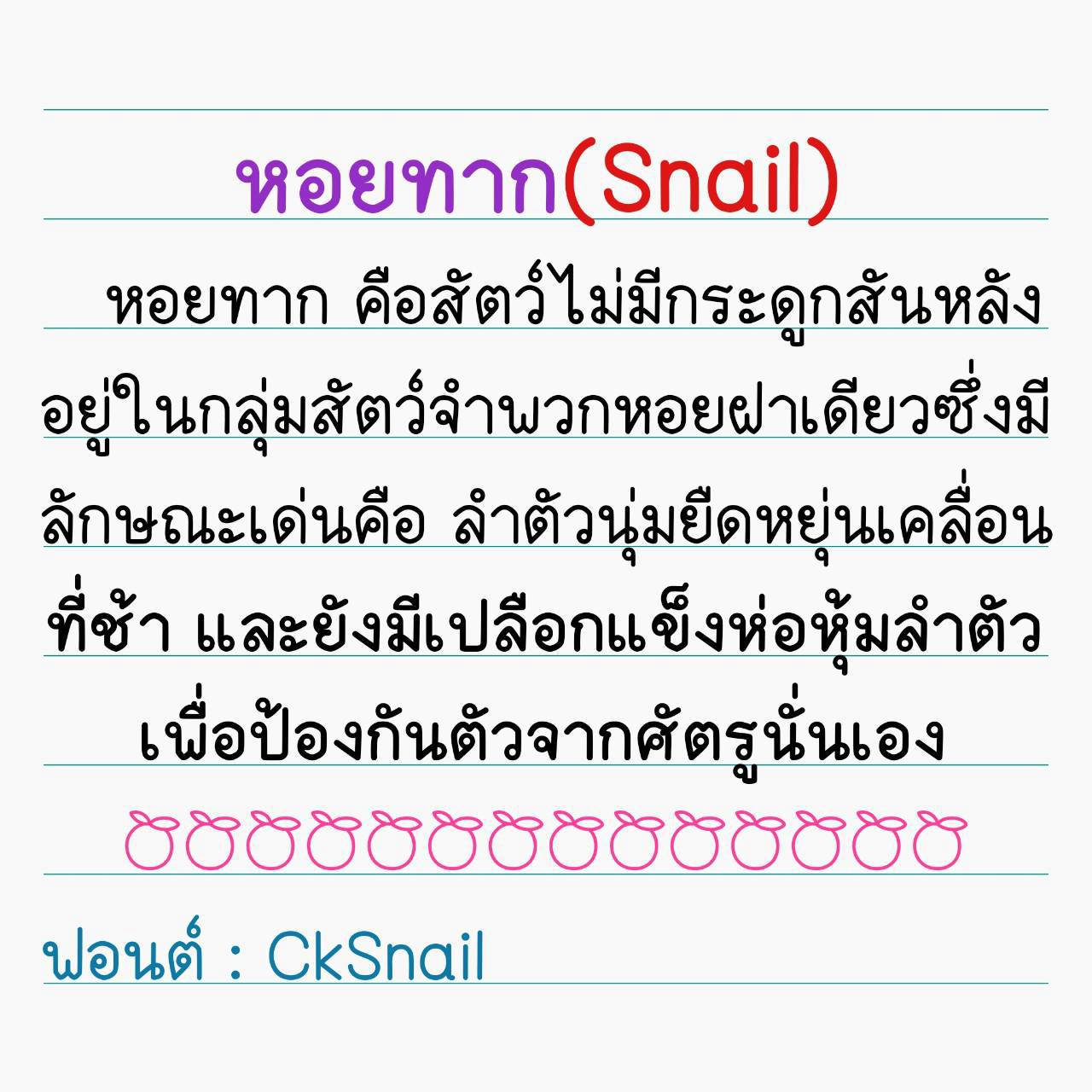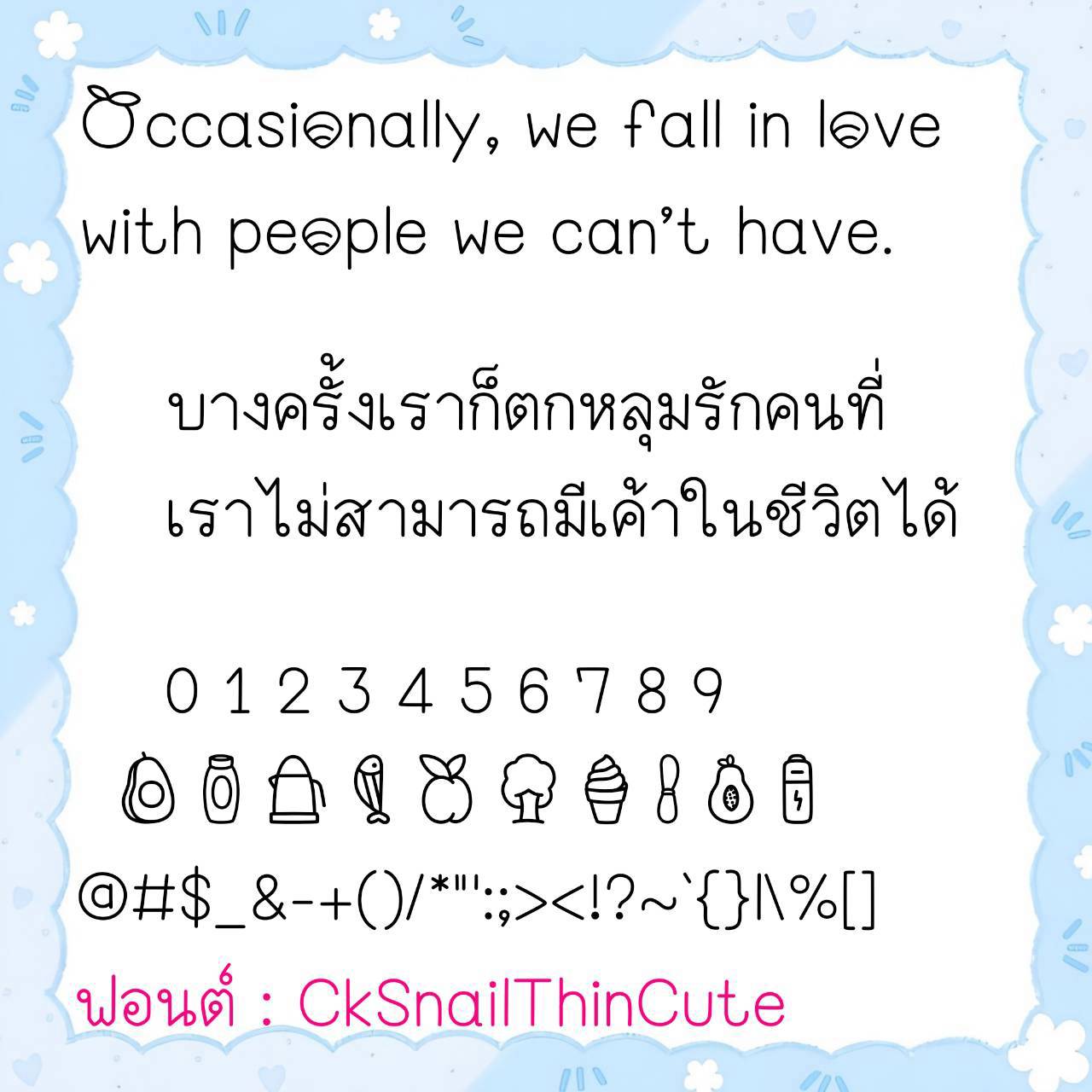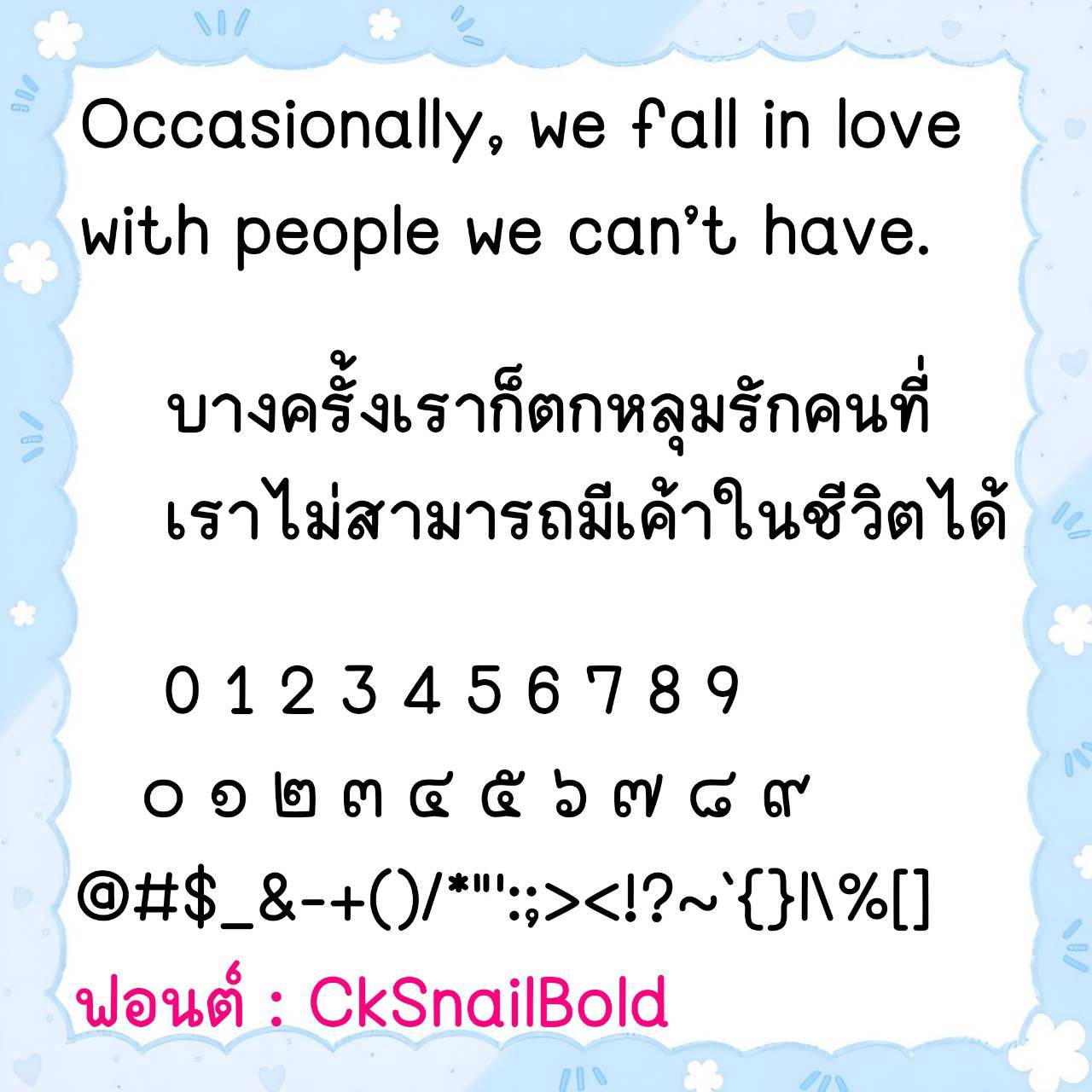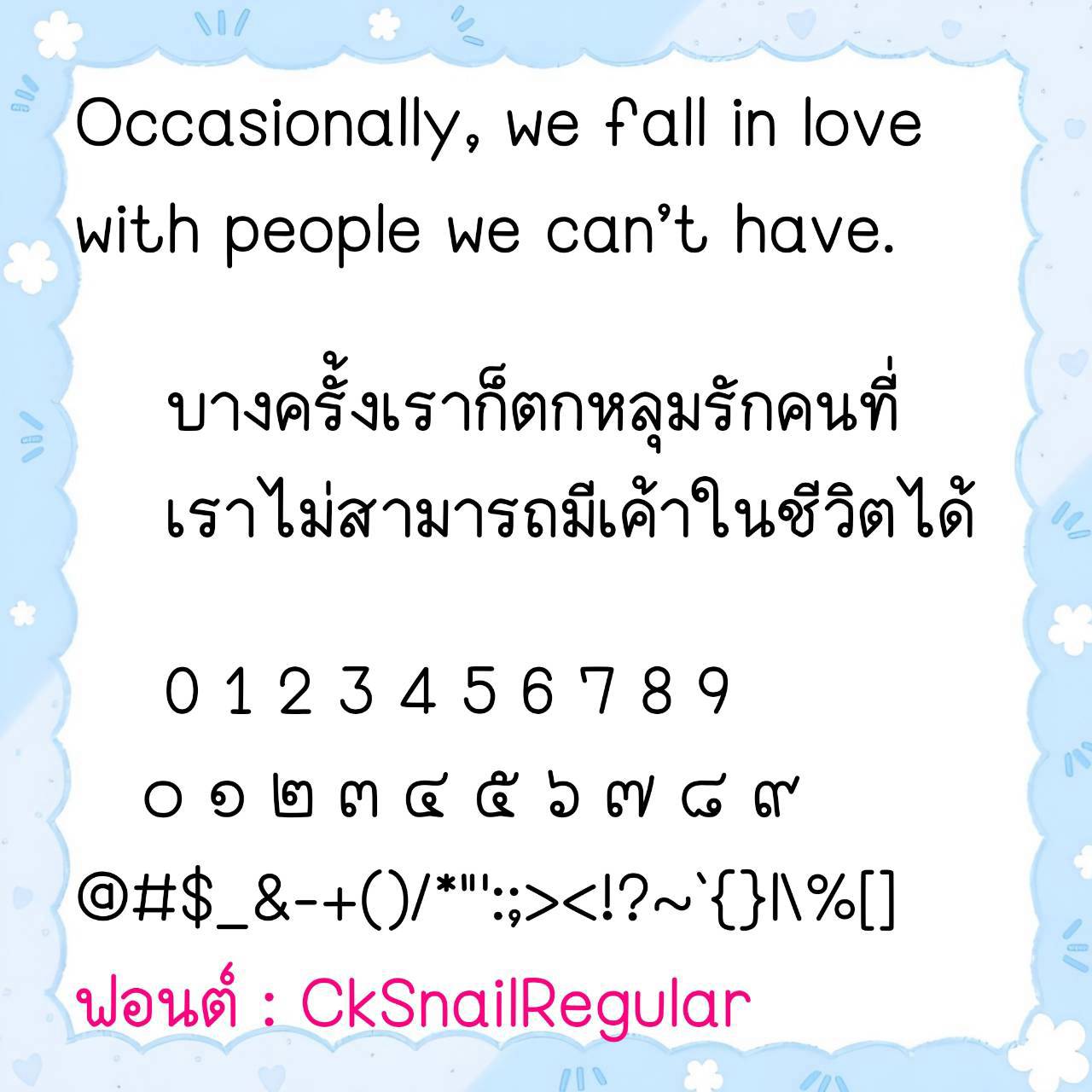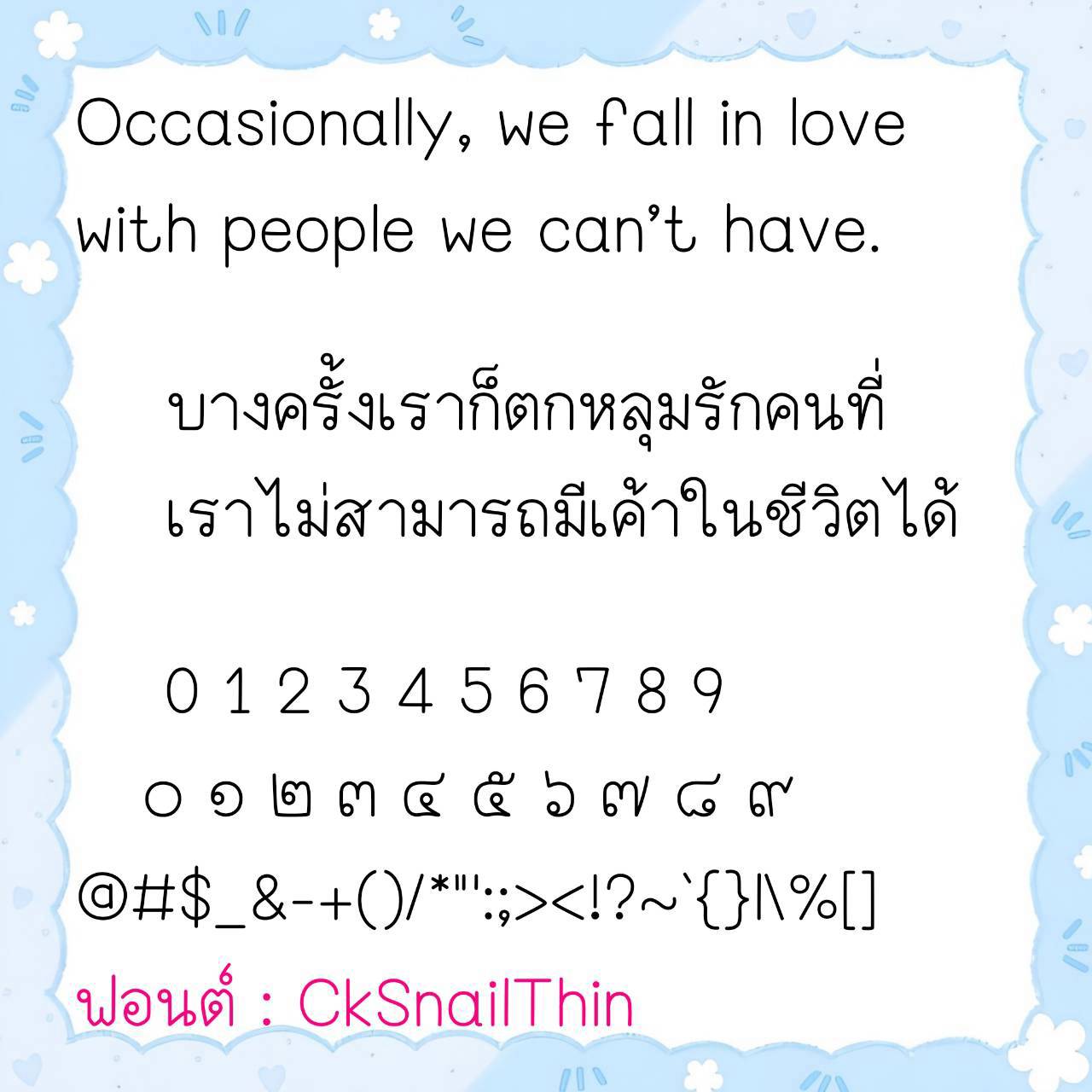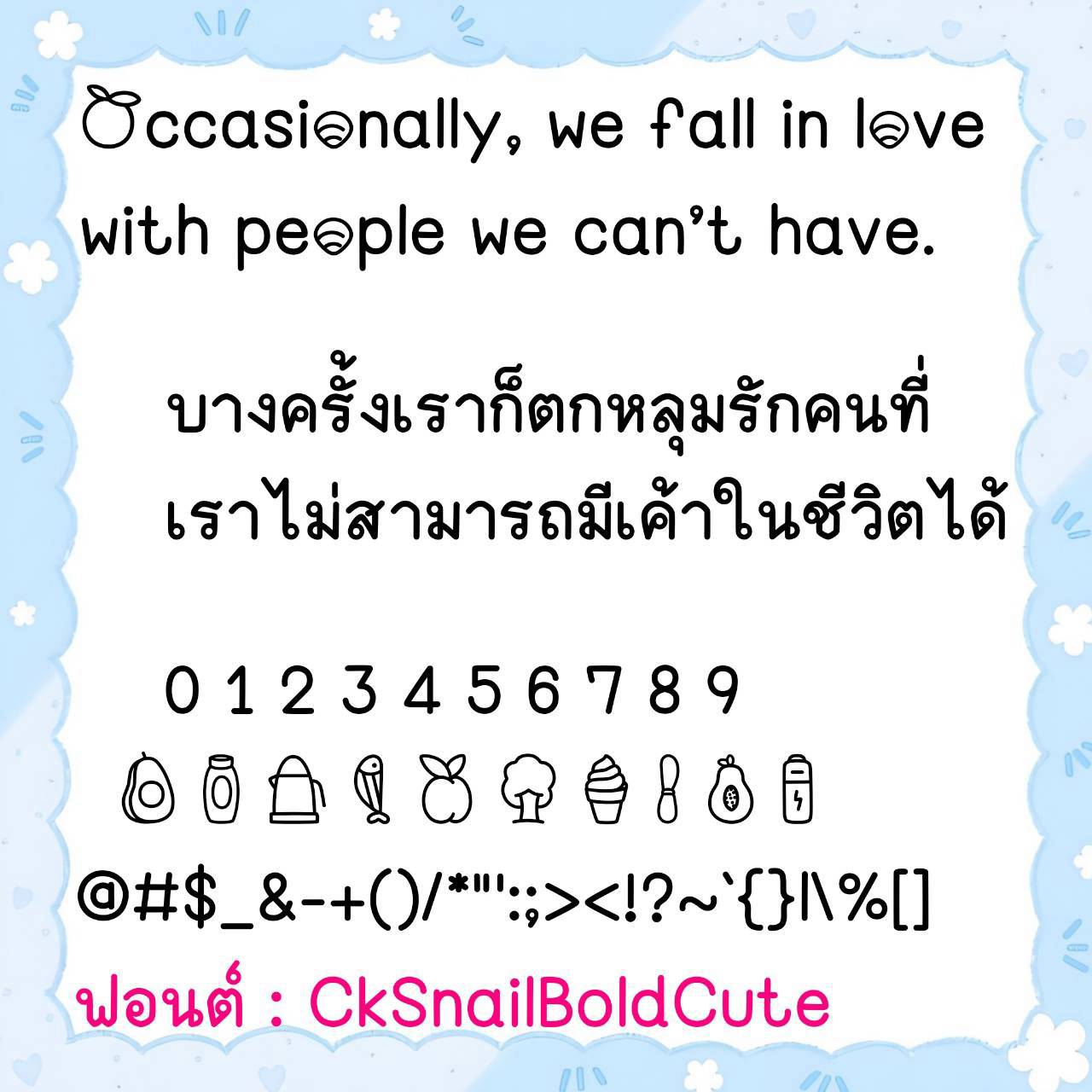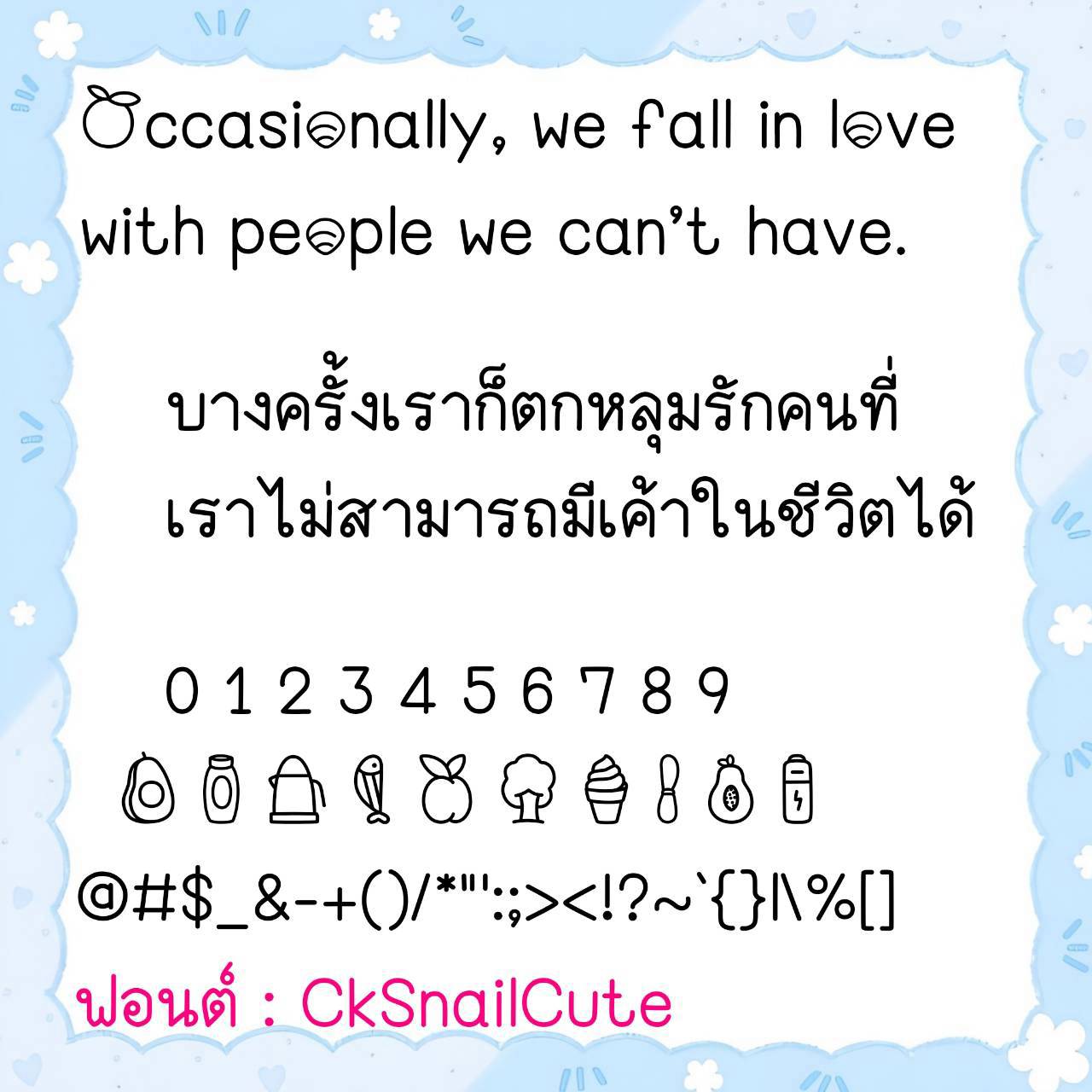
Font CkSnail
🔸 ฟอนต์ลายมือแนวเรียบร้อย ตัวเหลี่ยมแบบไทยคล้ายการคัดลายมือ เน้นความเป็นระเบียบอ่านง่าย และยังมีไฟล์อิโมจิน่ารักๆที่ใช้แทนเลขไทยให้ด้วยค่ะ 🥰💙
🔹 This is a neat, handwritten font with a square, Thai-style design similar to calligraphy, emphasizing order and readability. It also includes cute emoji files that can be used to replace Thai numerals. 🥰💙